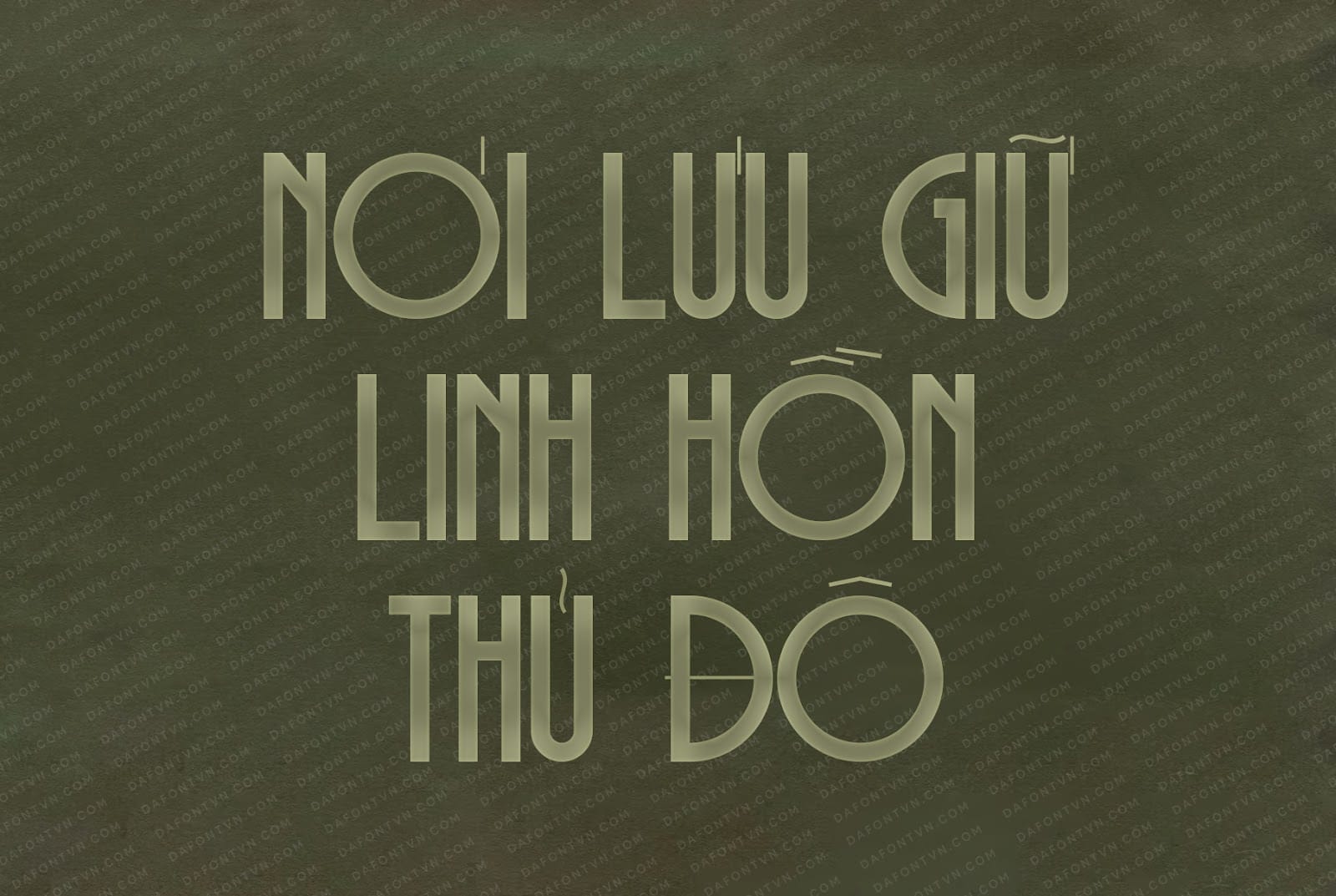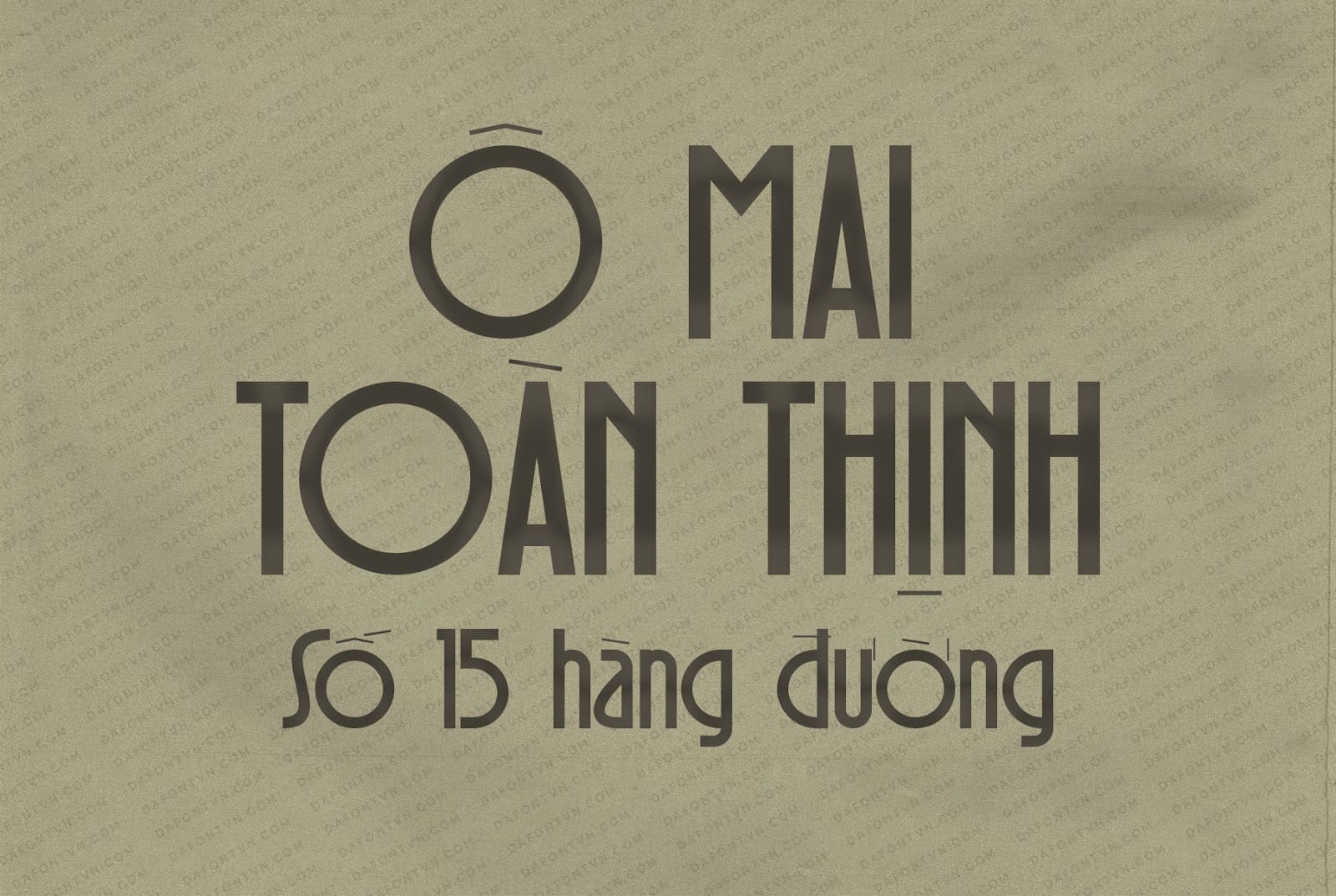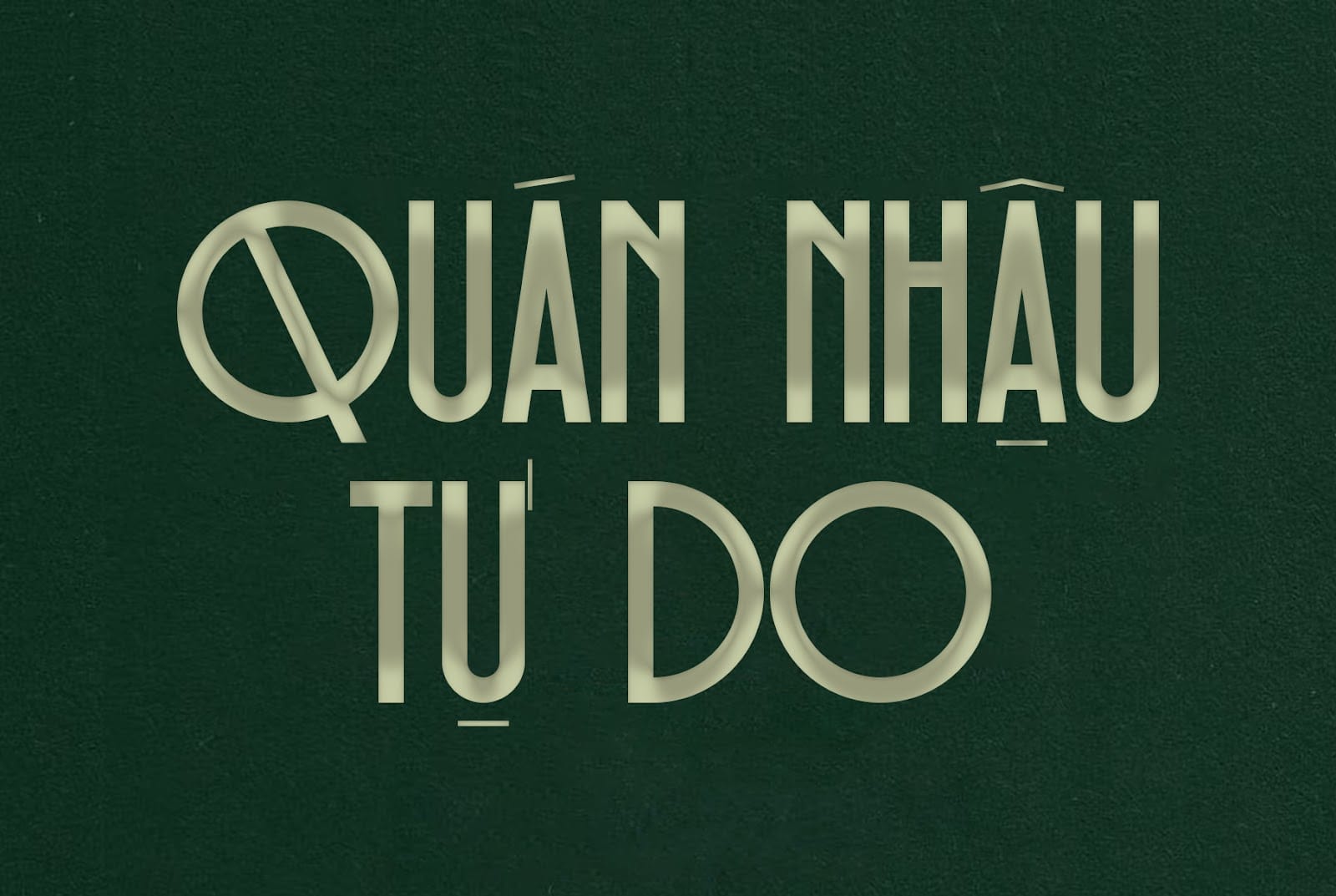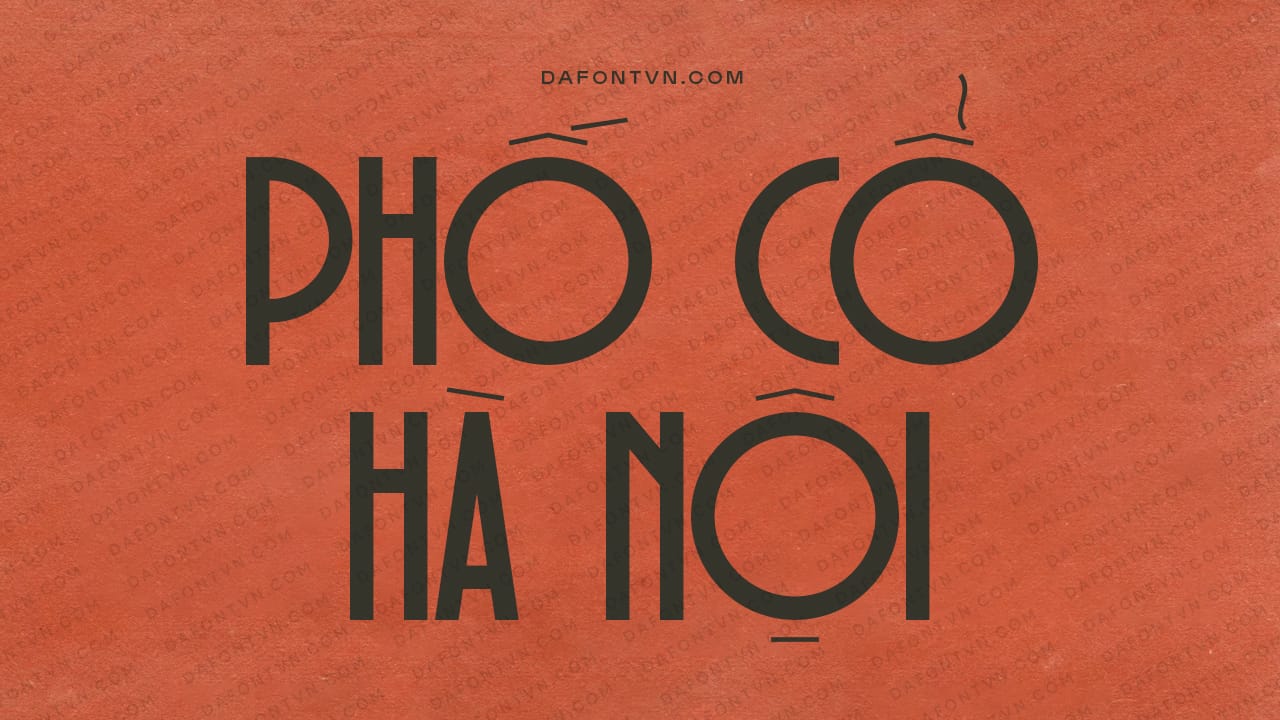
Guardilostra là một kiểu chữ vintage với các nét chữ được thiết kế độc đáo và thú vị. Nó được lấy cảm hứng từ các bảng hiệu, áp phích và bao bì thời xưa. Phông chữ này đã được tạo ra một cách cẩn thận để làm nổi bật mọi thiết kế cổ điển mà bạn đang hướng đến.
Guardilostra với các nét chữ cao đậm hoàn hảo cho mọi loại thiết kế như thiệp mời, tạp chí, logo, xây dựng thương hiệu, tiêu đề hoặc bất kỳ các thiết kế nào khác cần một kiểu font xưa cũ việt hóa đẹp mắt.
Các chữ cái mang phong cách cổ điển vì vậy nó được việt hóa với các dấu mang đậm hơi hướng của các biển hiệu thời xưa.